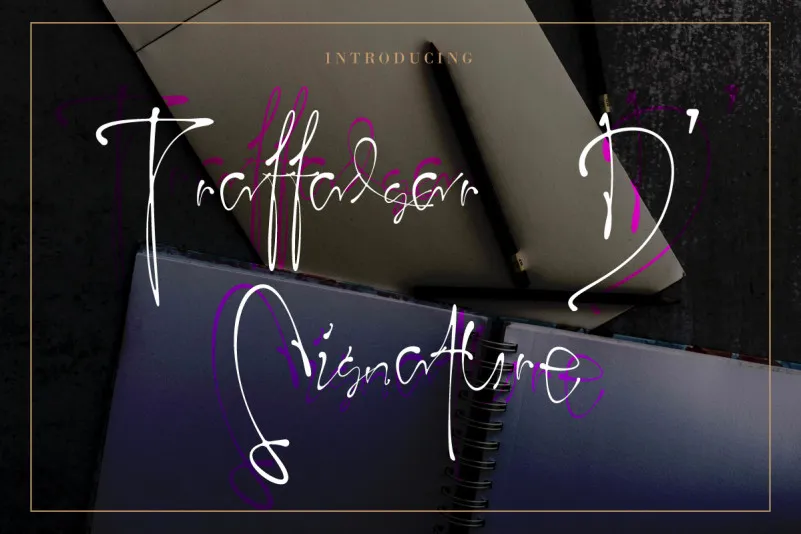
Traffalgar D’ Signature Font – Download Grátis
A ‘Traffalgar D’ Signature Font’ é uma elegante fonte de traço humanoizada com um estilo natural que se destaca por seu ar refinado e autêntico. Essa fonte perfeita para a personalização pessoal, ideal para ser usada como marca d’água ou em cartões de business, se tornou uma escolha inteligente para quem busca uma combinação única de sofisticação e naturalidade. Seu design delicado e aparentemente livre ressoa com um toque elegante que não apenas adicionará personalidade à sua identidade visual, mas também ajudará a criar um marca forte e memorável. A ‘Traffalgar D’ Signature Font’ é uma opção versátil que pode ser usada em diversos ambientes – seja para assinar documentos importantes ou construir o logotipo de uma marca inovadora. Ao adquirir esta fonte, você está incorporando a essência da IntrovArtZone ao seu design. Uma escolha inteligente poderia transformar um elemento insignificante num momento memorável que reflete sua identidade visual e traz vida à sua personalidade profissional.